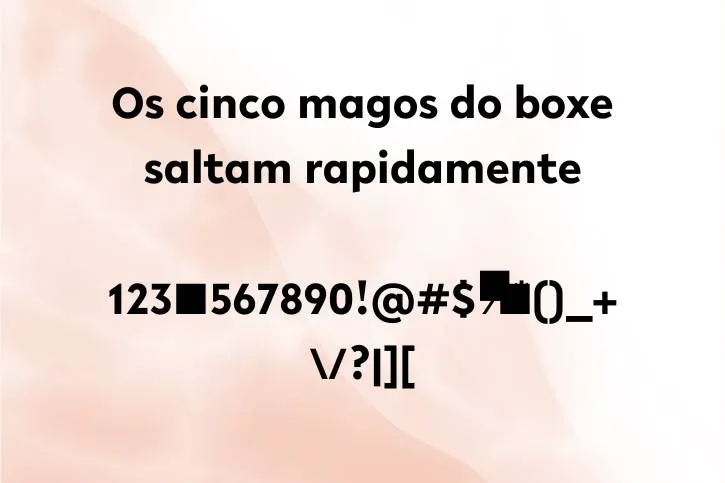
A fonte R-Flex é uma fonte moderna sem serifa com um toque geométrico e um pouco grotesco. Ele vem em 12 pesos, 6 retos e itálico correspondente. Cada peso inclui suporte estendido ao idioma (+ cirílico), frações, figuras tabulares, ligaduras e muito mais. Ele foi projetado com poderosos recursos de tipo aberto em mente.
Esta família de fontes é boa para combinar com a Fonte The Next, que é uma fonte sem serifa semelhante. Por ser uma fonte sem serifa, possui um design limpo e moderno, tornando-a adequada para uma ampla gama de aplicações de design gráfico. Uma das principais características é a legibilidade. Os personagens são cuidadosamente desenhados para garantir fácil leitura em diferentes tamanhos e contextos.
Além disso, ele vem em uma variedade de pesos e estilos, o que o torna extremamente versátil. Outro aspecto importante é a sua capacidade de adaptação a diferentes mídias e ambientes. Seja impressa ou na tela, a fonte mantém sua qualidade e legibilidade, garantindo uma experiência visual consistente em todas as plataformas.
Exibição da Fonte R-Flex
Melhores Recursos da Fonte R-Flex
Ele oferece uma variedade de recursos que o tornam uma escolha versátil e atraente para designers. Uma de suas principais características é a ampla gama de pesos e estilos, que permitem uma personalização detalhada para diferentes tipos de projetos. Seu formato limpo e moderno é adequado para uma variedade de aplicações.
Os designers podem usar a fonte Berling para criar designs mais elegantes. Outro destaque é a excelente legibilidade, mesmo em tamanhos menores. Além disso, possui personagens bem desenhados e proporções equilibradas, o que contribui para uma estética visualmente agradável.
Aplicativos que Usam a Fonte R-Flex
- Convites de festas infantis.
- Cartões de aniversário e saudações.
- Materiais escolares e educativos.
- Embalagens de produtos relacionados a confeitaria.
- Postagens em redes sociais com temáticas lúdicas.
- Criação de logotipos para negócios criativos.
- Decoração de festas e eventos temáticos.
- Projetos de artesanato e DIY.
- Páginas de scrapbook e álbuns de memórias.
- Elementos gráficos em websites e blogs divertidos.
Qual é a origem da fonte R-Flex?
É uma fonte moderna sem serifa com um toque geométrico e levemente grotesco, disponível em estilos elegantes.
Qual é a melhor característica da fonte de alimentação R-Flex?
Possui peso elegante, incluindo suporte estendido a idiomas (+ cirílico), frações, figuras tabulares, ligaduras e muito mais.